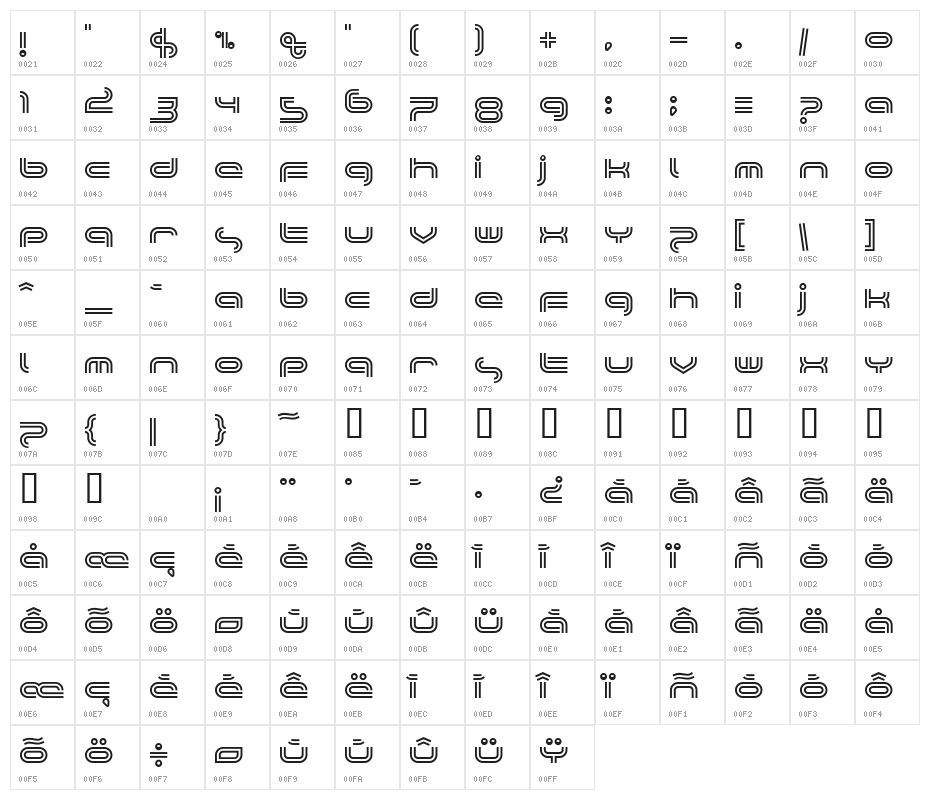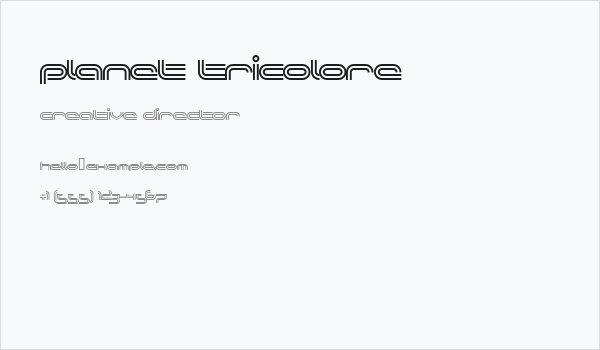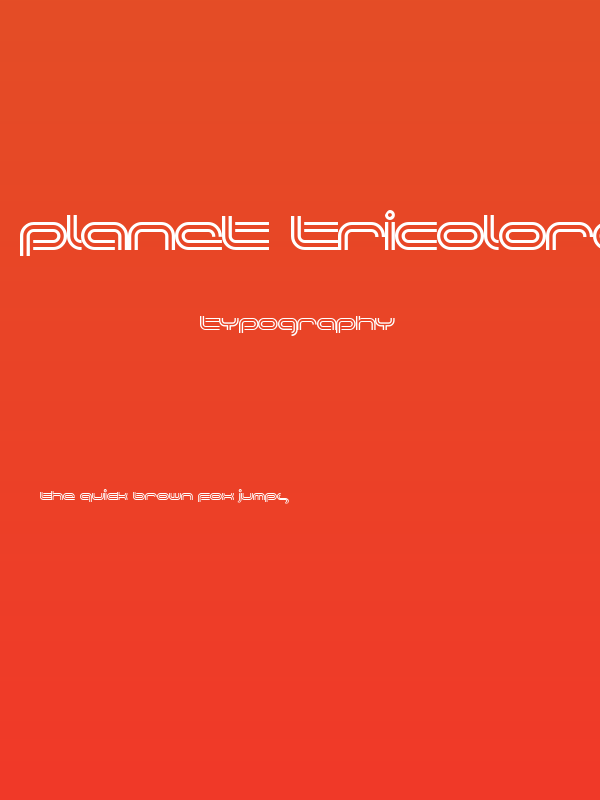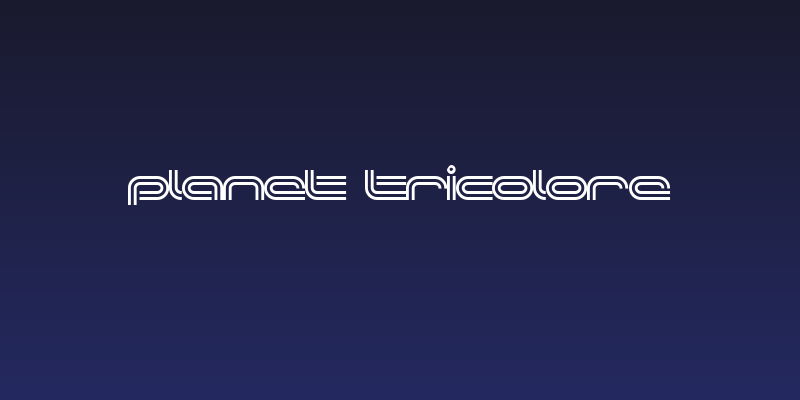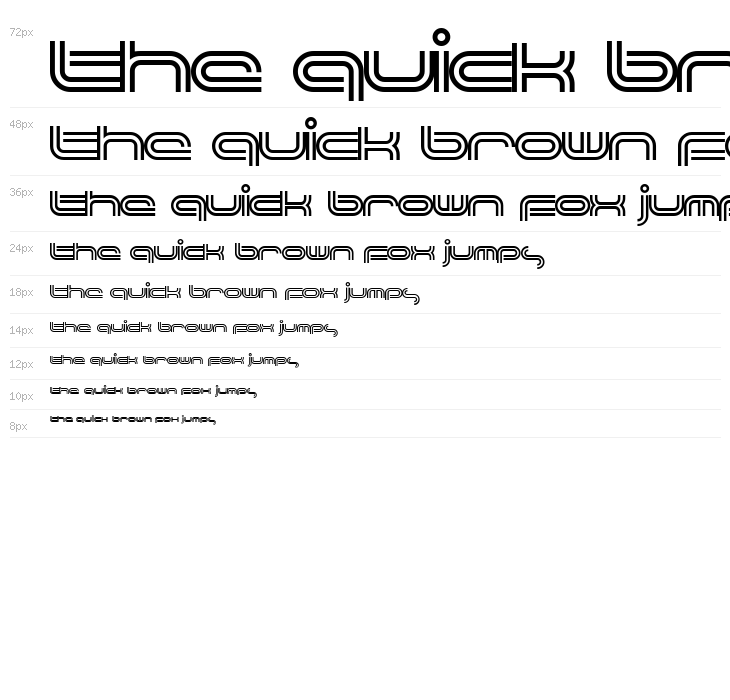
Planet TriColore Font
| مشاريع مقترحة | Ideal for sci-fi themed designs, tech branding, innovative product packaging, and modern digital interfaces. |